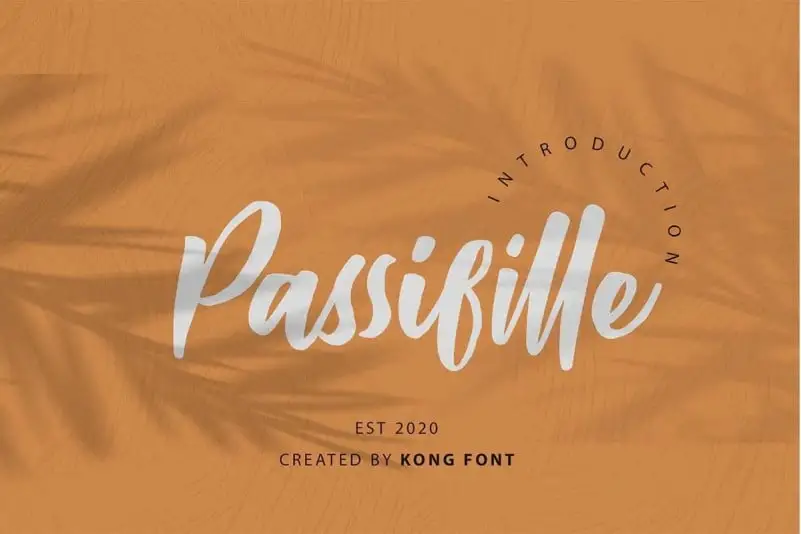
Passifille Script Font – Download Grátis
A Passifille Script Font é uma novidade que traz a beleza clássica do tipo script para um novo olhar moderno. Desenvolvida pelo 99designs, esta fonte apresenta um estilo sofisticado e elegante, perfeita para decorar textos de maneira única e impactante. Suas linhas fluidas e detalhes refinados criam uma sensação de elegância que se mistura perfeitamente com a contemporaneidade, tornando-a ideal para qualquer projeto gráfico que precise de um toque luxuoso e atual. Perfeito tanto para headlines quanto para subtítulos, essa fonte é certamente o companheiro perfeito para aqueles buscando uma fusão única de estilo clássico e moderno em seus designs.